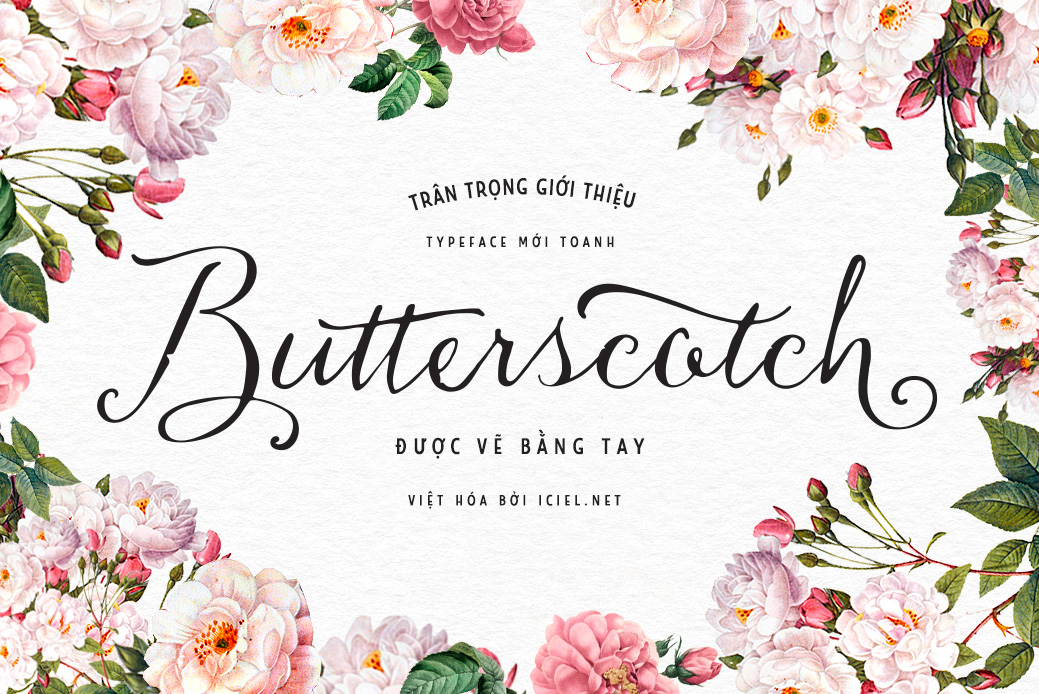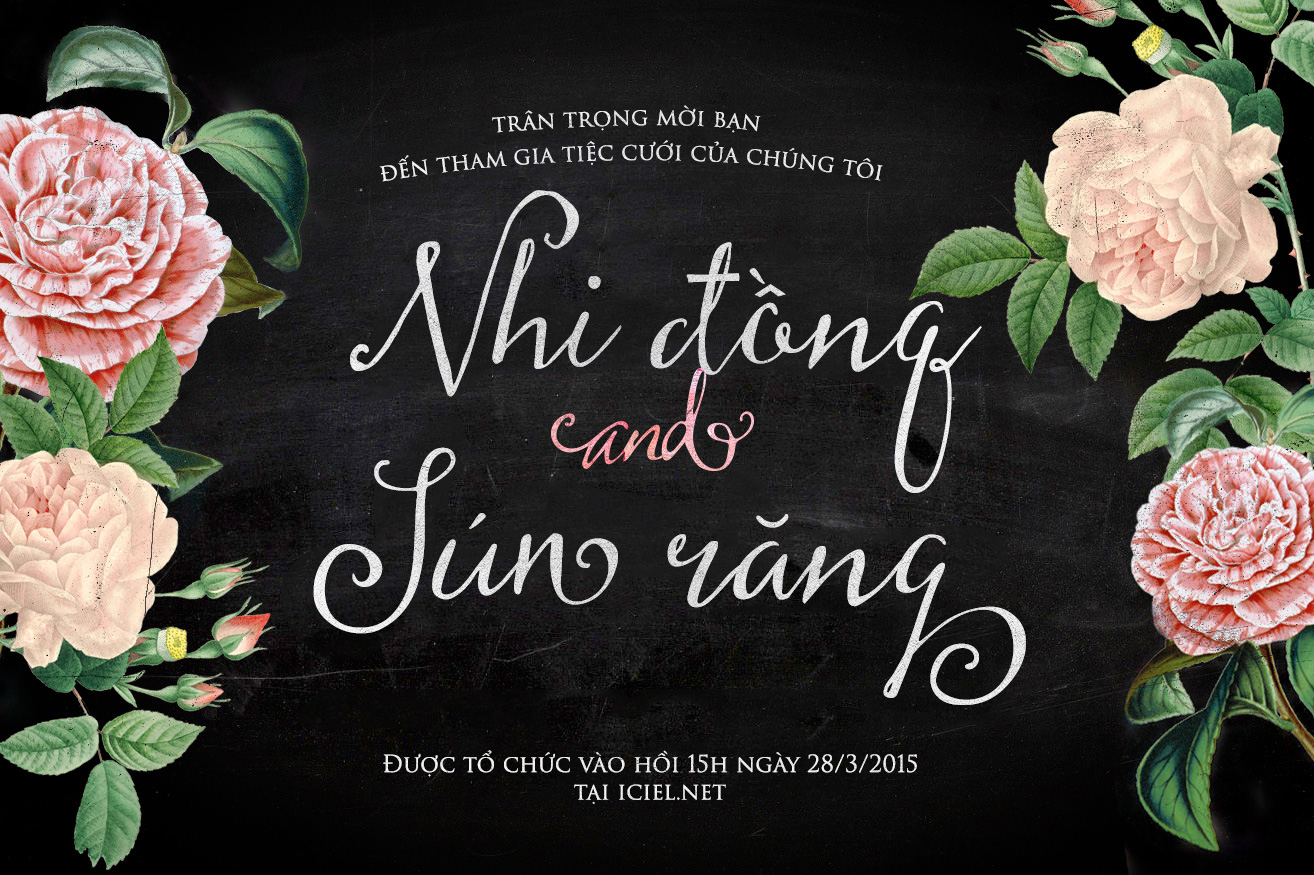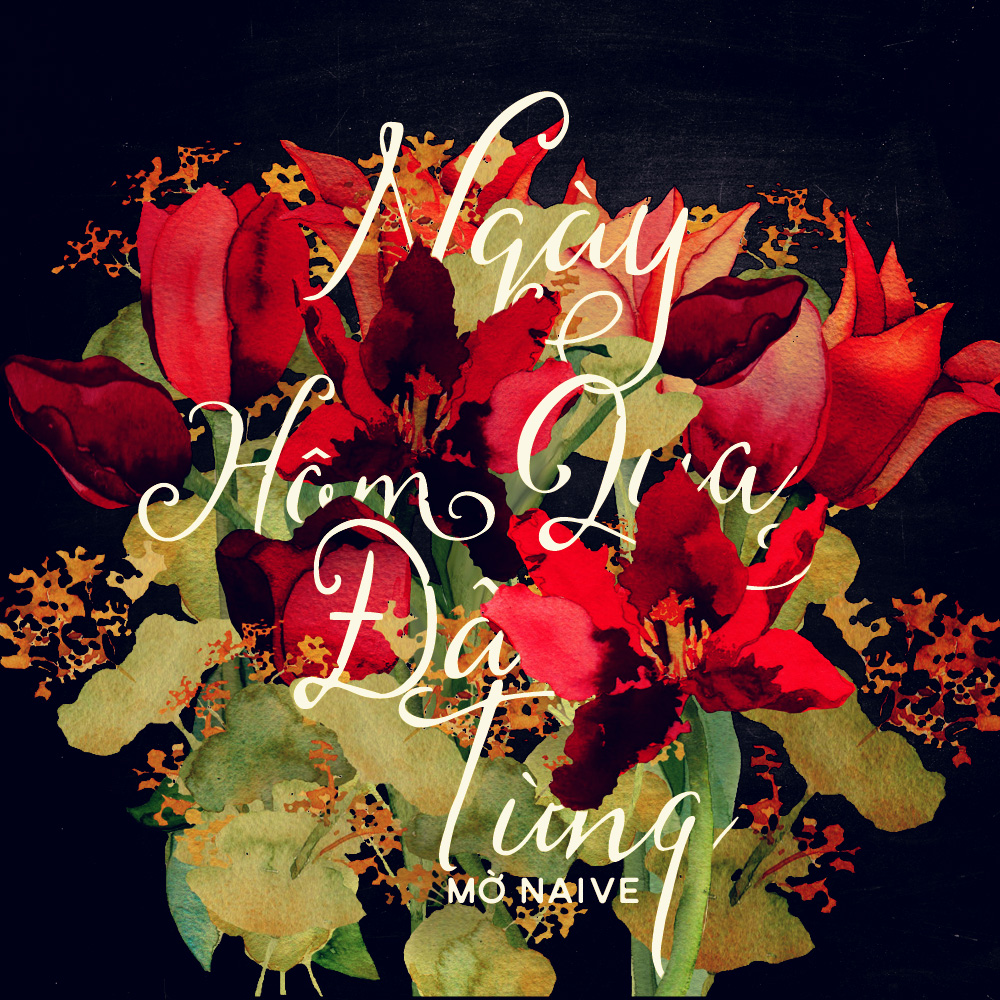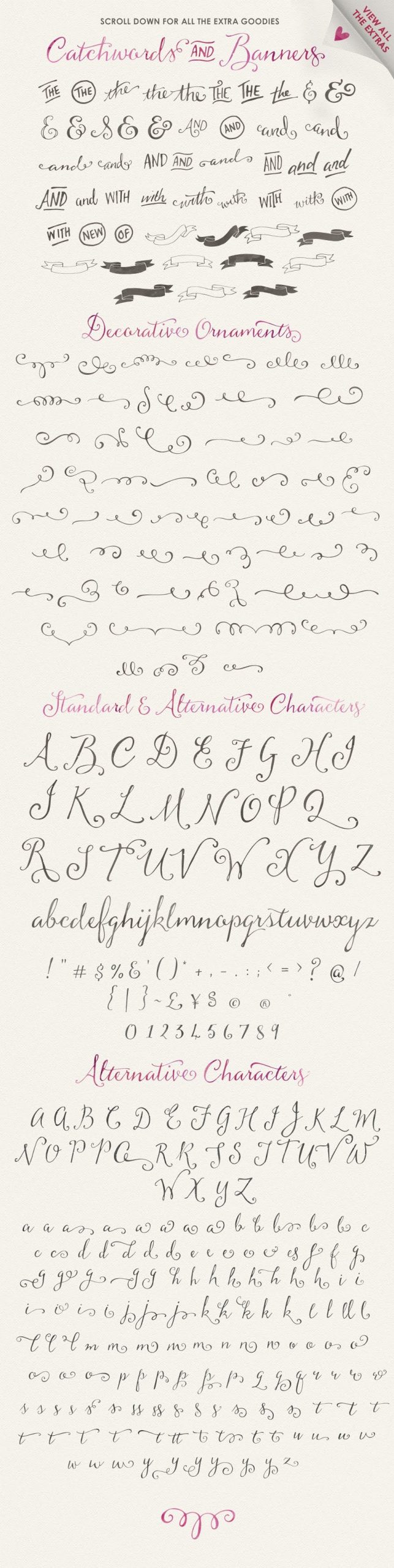
[Script] Font Butterscotch Việt Hóa
Font Butterscotch Việt Hóa là một typeface viết tay, mang phong cách handmade rất đẹp, được làm thủ công cẩn thận và sau đó được số hóa thành một kiểu chữ dễ sử dụng, thanh lịch nhưng cực kỳ ấn tượng. Font được Việt Hóa bởi iCiel.